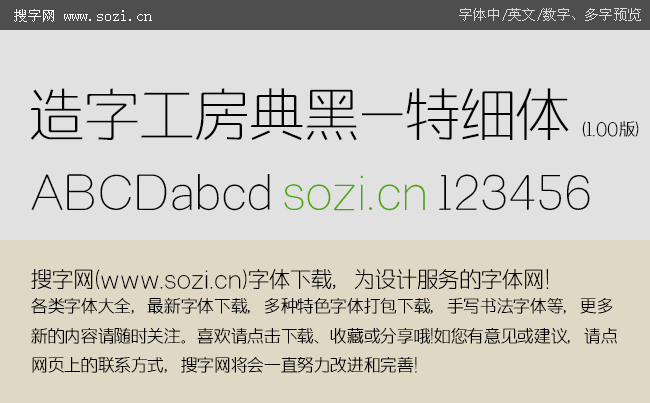
造字工房典黑特細(xì)體
搜字網(wǎng)給大家提供一款造字工房典黑特細(xì)體中文字體下載。造字工房典黑字形方正嚴(yán)謹(jǐn)、筆畫(huà)簡(jiǎn)潔有力、中宮清晰,在黑體字形基礎(chǔ)之上巧妙創(chuàng)新,使其字形筆畫(huà)柔和而不失剛毅,風(fēng)格鮮明且極具易讀性。并具有極強(qiáng)的時(shí)尚感。此款字體適用于文字排版、廣告設(shè)計(jì)、企業(yè)宣傳等視覺(jué)環(huán)境,有著極強(qiáng)的應(yīng)用空間。